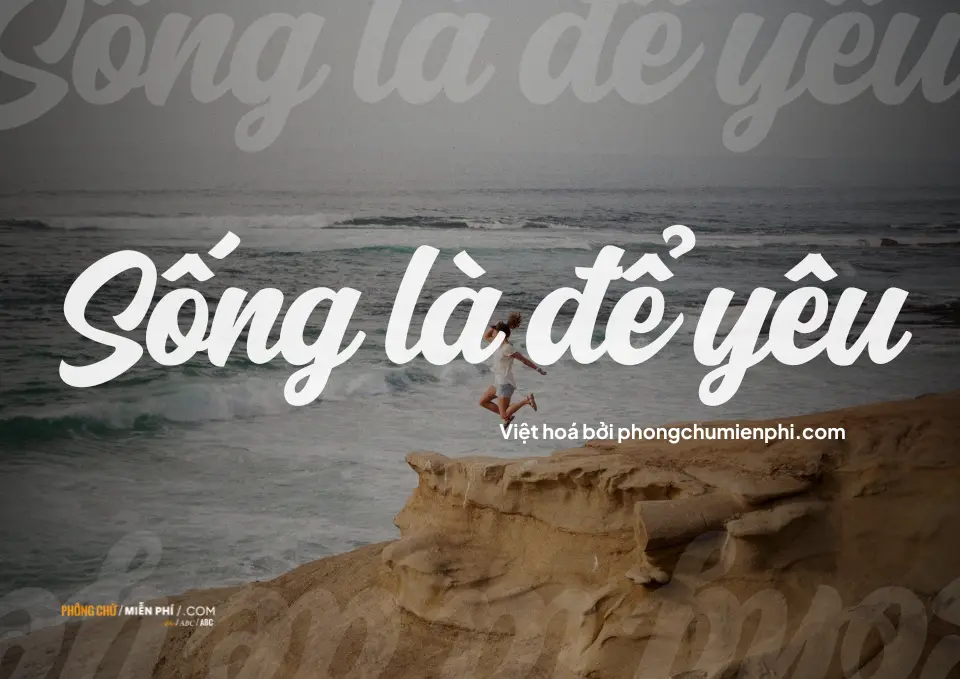
Tên font: Font Việt hoá AIRATES SCRIPT
Font Việt hoá PCMP AIRATES SCRIPT được việt hoá với phông chữ miễn phí.
PCMP Airates Script Fonts là font chữ đầu tiên mà tác giả giới thiệu ra thế giới. Lấy cảm hứng từ một bộ phim kể về hành trình của một người mất tất cả nhưng vẫn kiên cường tìm lại ý nghĩa cuộc sống – nơi câu chuyện bắt đầu được tái sinh ở tận cùng thế giới.
Đây là font chữ Việt hóa dạng script với nét chữ dày, dễ đọc, mang lại cảm giác thoải mái khi sử dụng. Phông chữ miễn phí này phù hợp cho nhiều mục đích thiết kế như logo, huy hiệu, bao bì, tiêu đề, poster, áo thun, thiệp chúc mừng, danh thiếp, thiệp cưới và nhiều hơn nữa. Các ký tự mềm mại, uyển chuyển giúp tạo nên những thông điệp nổi bật và đầy cuốn hút.
Bạn có thể mix & match với nhiều ký tự thay thế để phù hợp với dự án của mình, đặc biệt ấn tượng hơn khi kết hợp với các swash hoặc swash thay thế. Bộ ký tự thay thế này được chia thành nhiều tính năng OpenType như Stylistic Alternates, Ligature và Ligature Alternates, mang lại sự linh hoạt tối đa cho thiết kế của bạn.